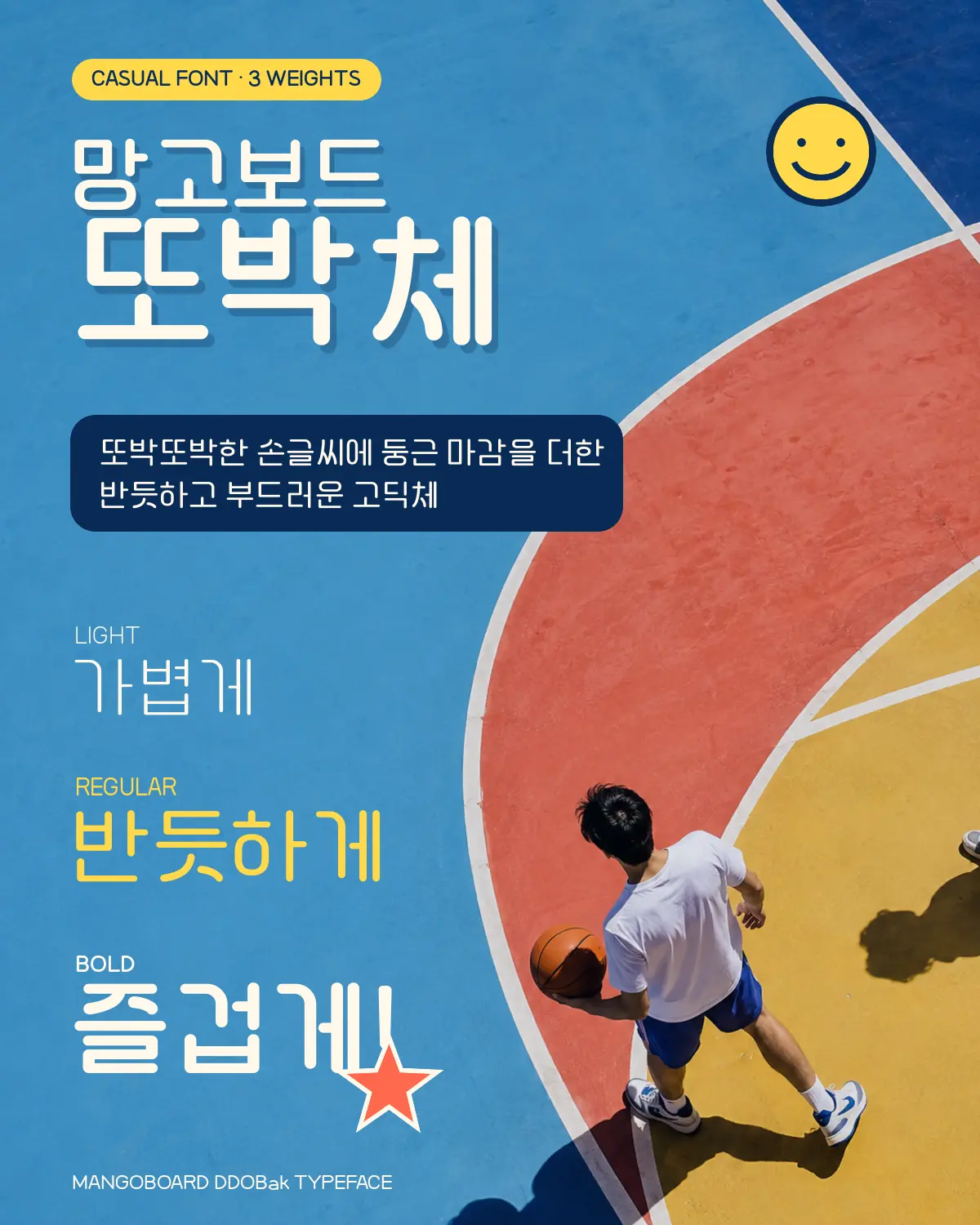
망고보드 또박체 — (주)리아모어소프트에서 배포하는 무료 폰트입니다. 또박또박한 손글씨 느낌에 둥근 마감을 더해 반듯하고 부드러운 인상을 주는 고딕체
디자인 도구 망고보드를 만드는 리아모어소프트가 개발한 서체입니다. 망고보드 안에서 쓰이면서 PC로 내려받아 쓸 수도 있게 배포하고 있습니다.
소개 문구가 이 서체의 위치를 잘 설명합니다. 또박또박 반듯하게 쓴 손글씨 느낌의 서체인데 고딕 비례를 활용해 가독성을 높였고, 획 끝을 둥글게 마무리해 귀여운 느낌을 더했다는 것입니다. 손글씨의 인상은 가져오되 골격은 고딕을 따랐다는 뜻이라, 같은 손글씨 계열보다 글줄이 안정적입니다. 낱자가 가로로 넓게 퍼진 것도 특징입니다.
굵기는 Light와 Regular, Bold 세 가지로 본문용으로 쓰기에 충분합니다. 폰트픽이 서비스하는 파일은 현대 한글 11,172자를 모두 담고 있습니다. 카드뉴스나 프레젠테이션, 교육 자료의 본문에 두루 쓸 수 있습니다.